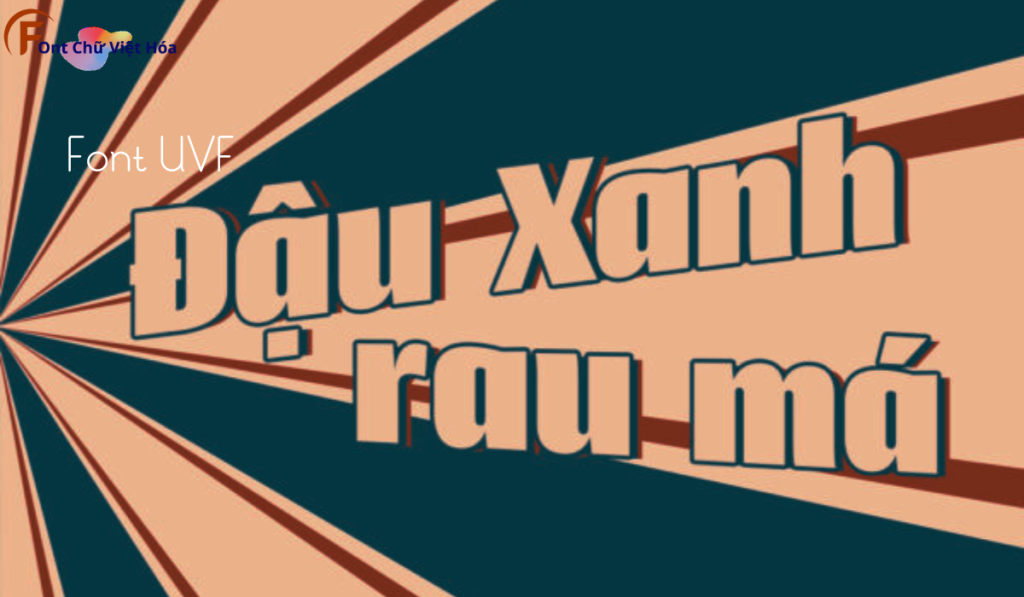
Font MJ Grueso Việt Hóa
Tác giả: MJ Design
Font MJ Grueso Việt Hóa là một font chữ không chân mạnh mẽ, thuộc bộ font MJ. Được thiết kế với mục tiêu mang lại sự nổi bật và ấn tượng, font này lý tưởng cho các dự án thiết kế như tiêu đề, quảng cáo, và bao bì sản phẩm. Với các nét chữ đậm và chắc chắn, Font MJ Grueso Việt Hóa không chỉ dễ đọc mà còn tạo cảm giác mạnh mẽ và quyết đoán. Việc Việt hóa font giúp người dùng dễ dàng sử dụng trong các thiết kế tiếng Việt, mang lại sự tiện lợi và thẩm mỹ cao.